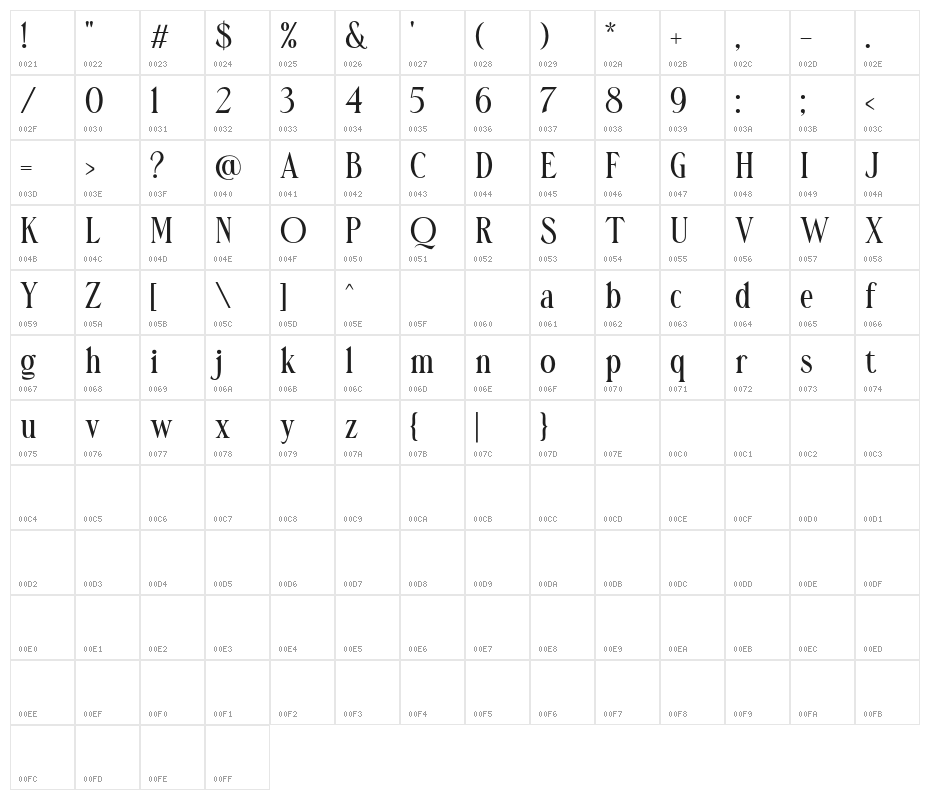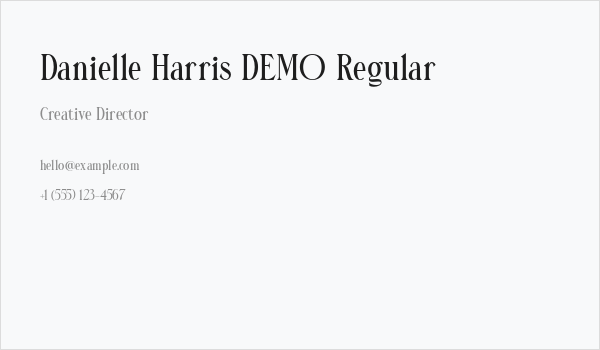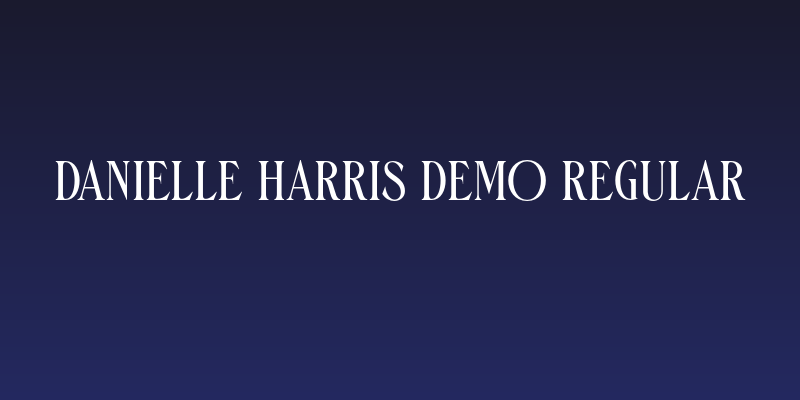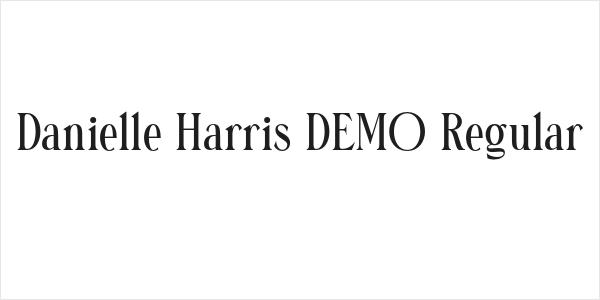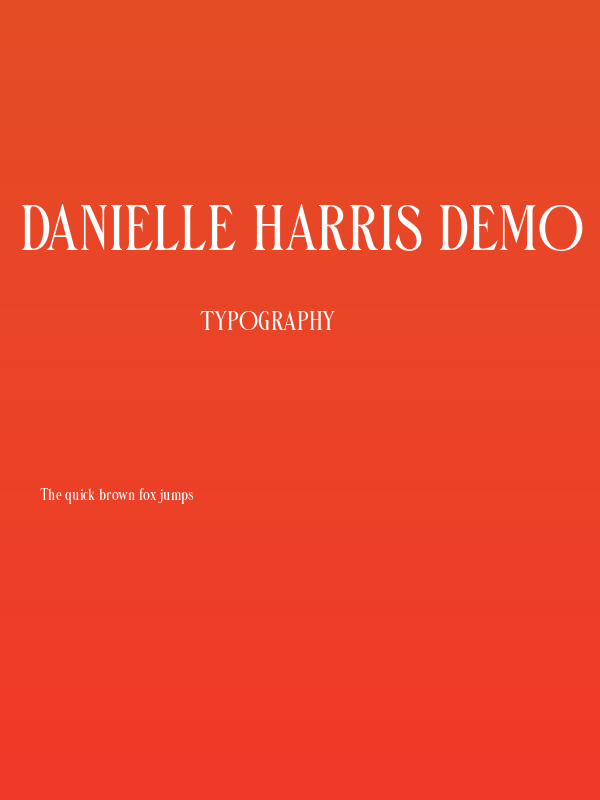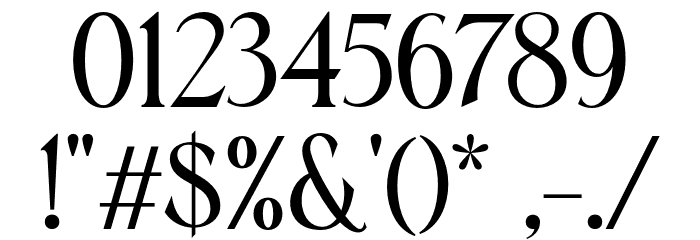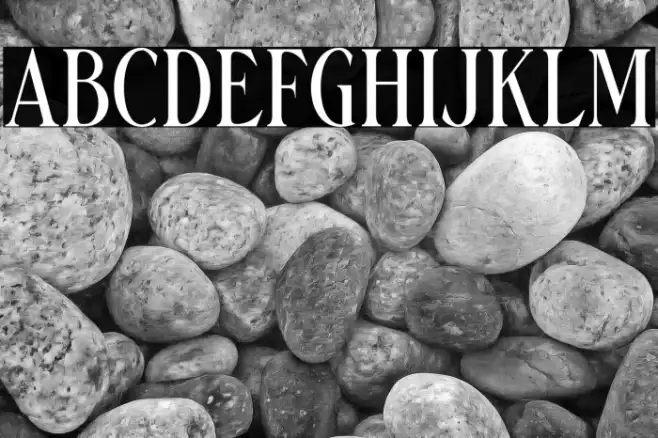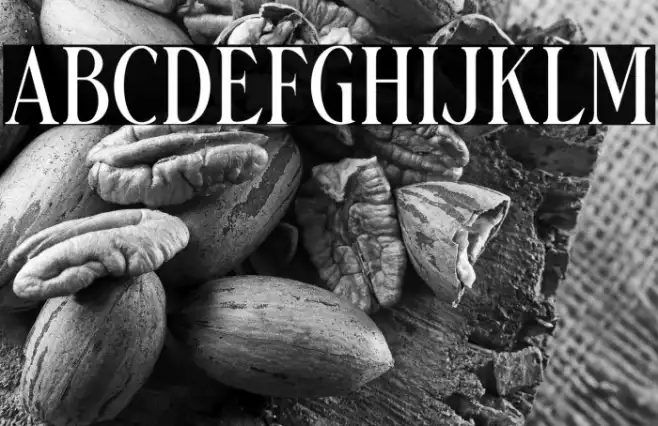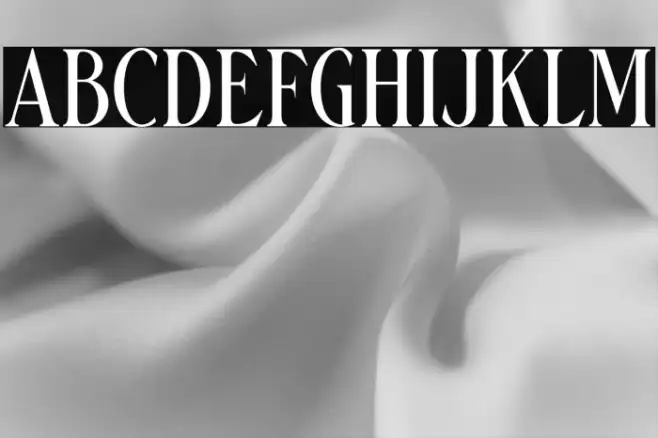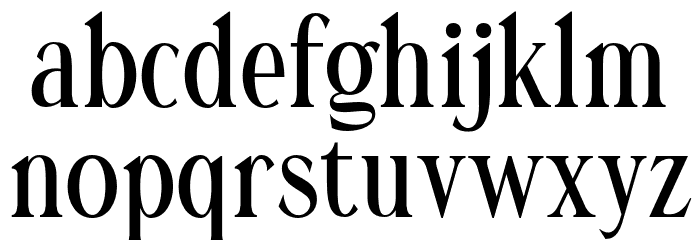
Danielle Harris DEMO Regular Font
✎ Serif
| Categorías | Serif |
| Estilo general | Classic |
| Caso de uso | Headlines, Body text, Logos |
| Proyectos propuestos | Ideal for editorial design, book covers, formal invitations, and branding projects that require a touch of elegance and sophistication. |